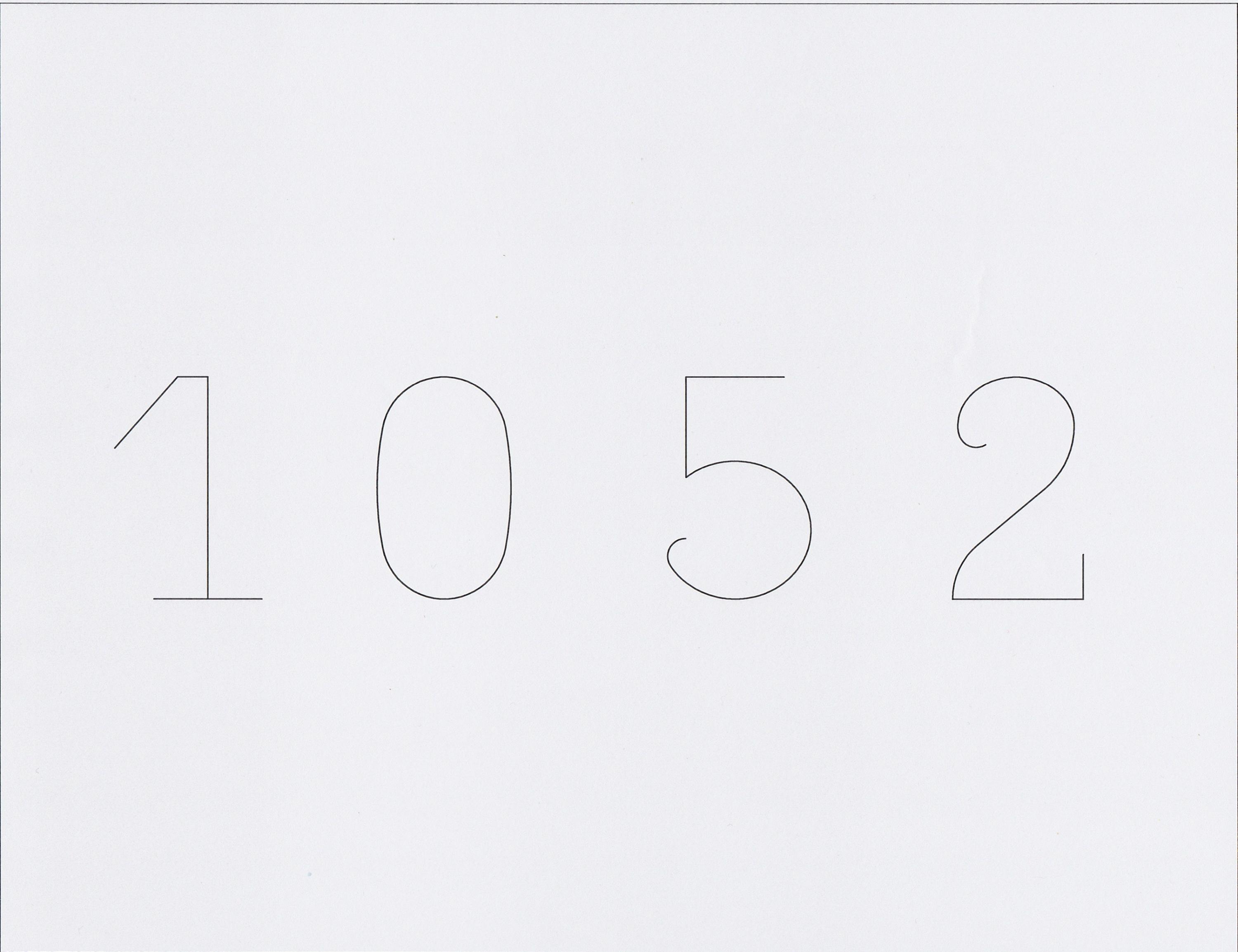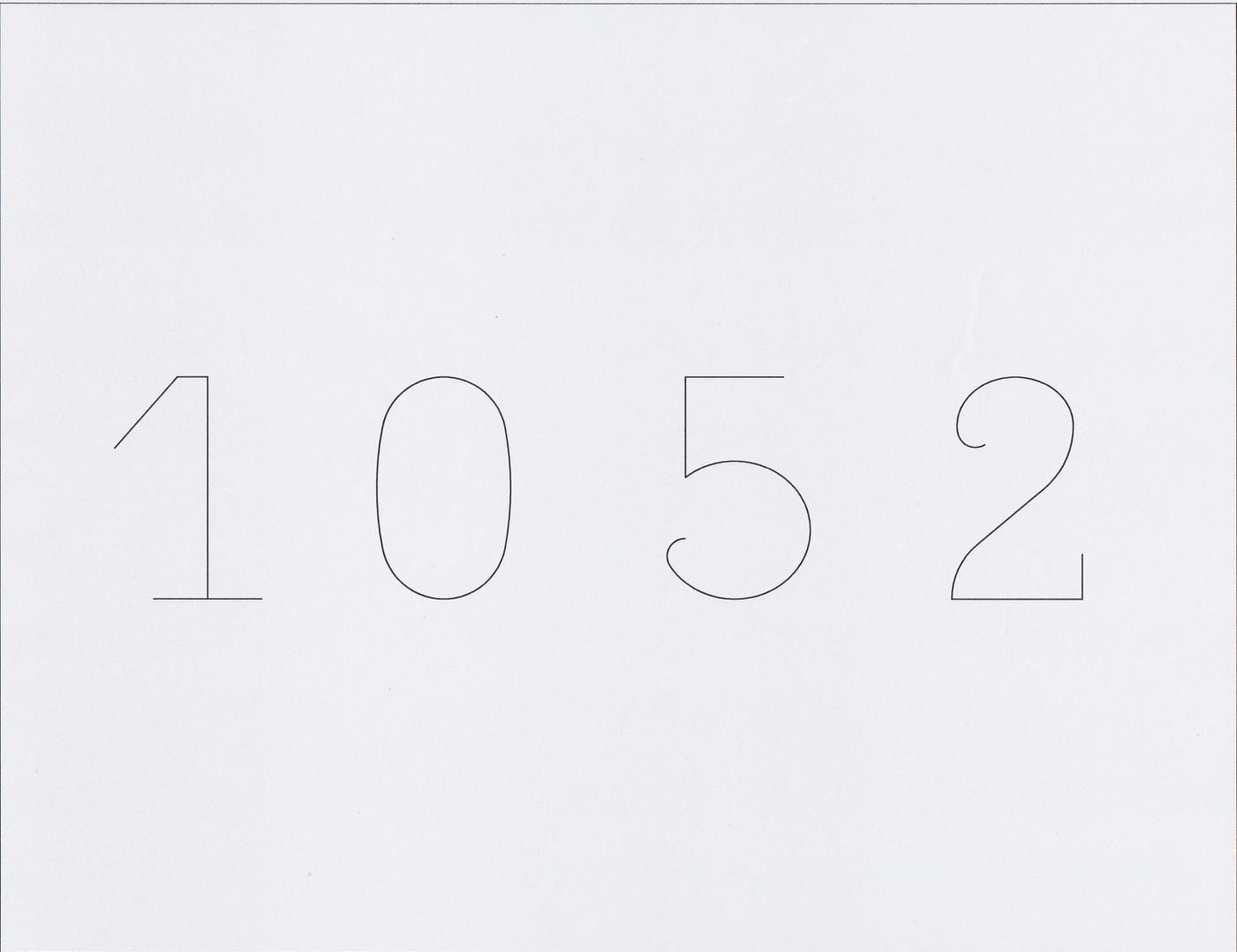
Zu welcher Schriftart gehören diese Zahlen?
Ich habe sie auf einem antiken Jagdgewehr gesehen
und sie mit Hilfe von AutoCad nachgezeichnet.
Das Gewehr stammt von ca. 1920 bis 1930.
Zu welcher Schriftart gehören diese Zahlen?
Vermutlich zu gar keiner. Wir meinen mit Schriftarten ja meist feststehende Entwürfe, die man von Schriftanbietern kaufen/lizenzieren kann bzw. früher einmal konnte. Und es sind diese frei verfügbaren Schriften, die dann Schrift-Namen bekommen.
Wie der obige Hersteller seine Gewehre beschriften hat weiß ich nicht. Gut möglich die Stempel wurden in deren Fabrik angefertigt und waren nie anderweitig verfügbar und mussten daher auch nicht mal mit irgendeinem Schriftnamen versehen werden.
Und auch wenn diese Prägeziffern von einer Spezialfabrik für derartige Stahlstempel gefertigt wurden, wurde gerade bei den Ziffernsätzen für Waffen ein besonderwer Zahlensatz entworfen, um ein fälschen/verfälschen der Seriennummer zu erschweren. Dies gilt übrigens auch für die Prägezuiffern für Motor-und Fahrgestellnummern an Kraftfahrzeugen, die sich ja auch von Hersteller zu Hersteller leicht unterscheiden.